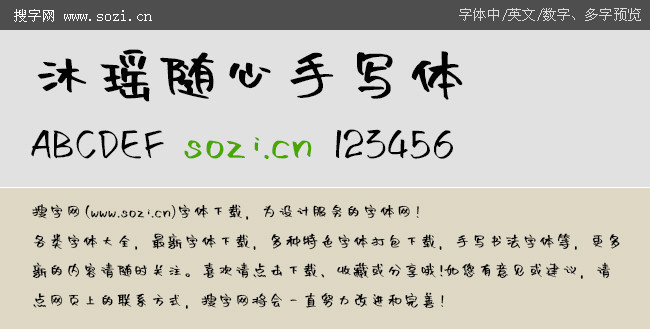
沐瑤隨心手寫體
搜字網(wǎng)提供一款免費(fèi)可商用的沐瑤隨心手寫體中文字體下載,沐瑤隨心手寫體是一款由網(wǎng)名春顏秋色的設(shè)計(jì)師以女兒名字命名的第二款手寫字體,并提供給大家免費(fèi)商用。這款字體休閑可愛,適合兒童包裝設(shè)計(jì),網(wǎng)頁設(shè)計(jì),海報(bào)設(shè)計(jì)等場合使用。